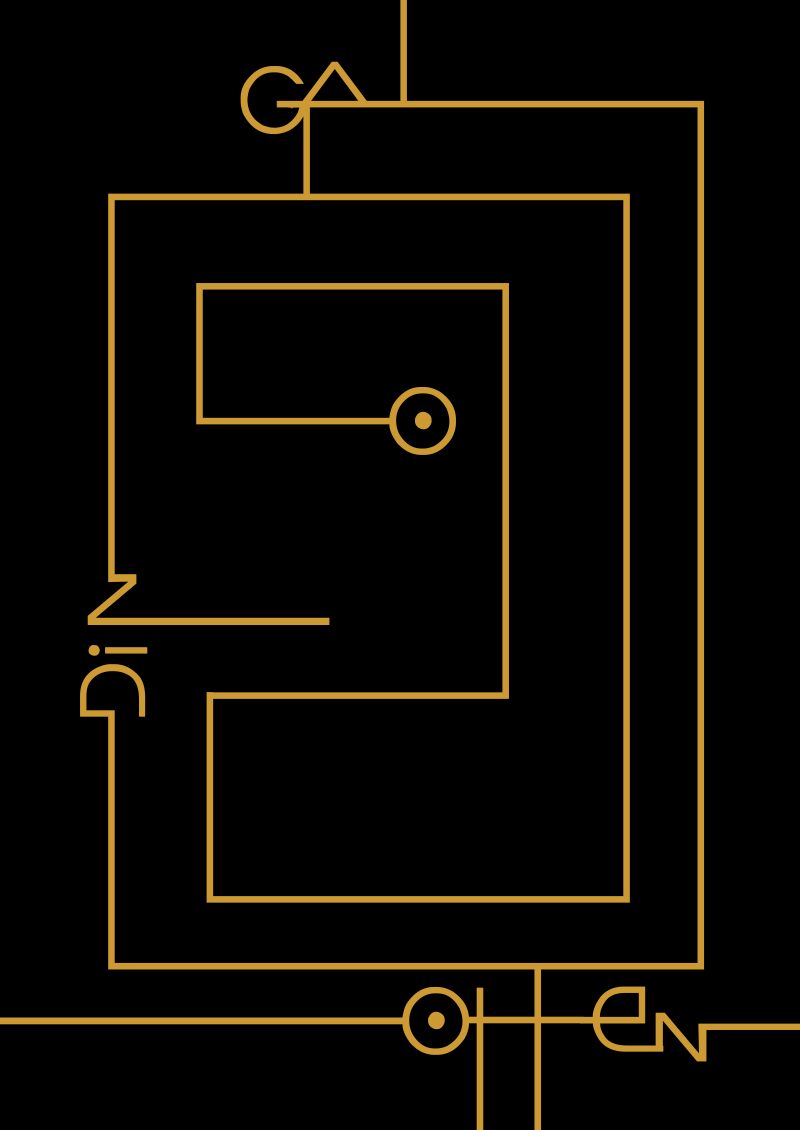
Stretched Signature Flex, którego autorem jest Galdino Otten, to darmowy, futurystyczny krój piśmienniczy typu display o jednolitym śladzie, z ekstremalnie wysokimi pociągnięciami i szerokimi, okrągłymi łukami. Konstrukcja o włoskowatej grubości i nagłe poprzeczne belki nadają literom architektoniczny, schematyczny charakter.
Projektanci działający w obszarze technologii i kultury eksperymentalnej mogą wykorzystać go do plakatów wydarzeń, opraw albumów, grafik cyfrowych oraz w identyfikacji wizualnej mody. Wydłużone linie mogą nawiązywać do ścieżek obwodów, siatek map lub ilustracji schematycznych, czyniąc tytuł częścią otaczającego obrazu.
This font was conceived according my self signature that you can see in all my artwork in my blog as well street art writings, and the it can be used in diverses ways and artstylles, it can be used of the simplest the most sophisticated work until. Its more important characteristic is the flexibility of its connections, for being linked becomes infinitely flexible being able to transpose the limitations of any space.